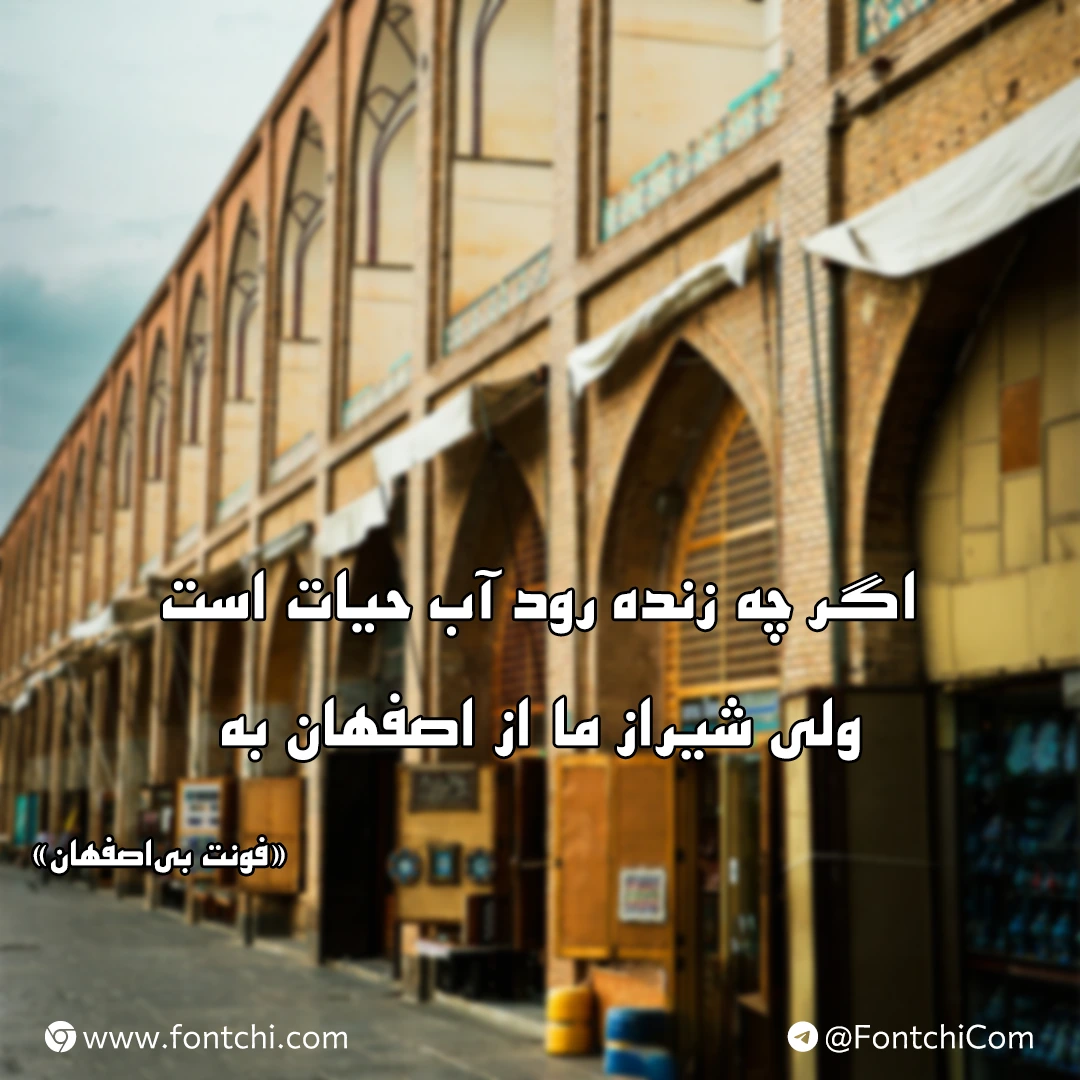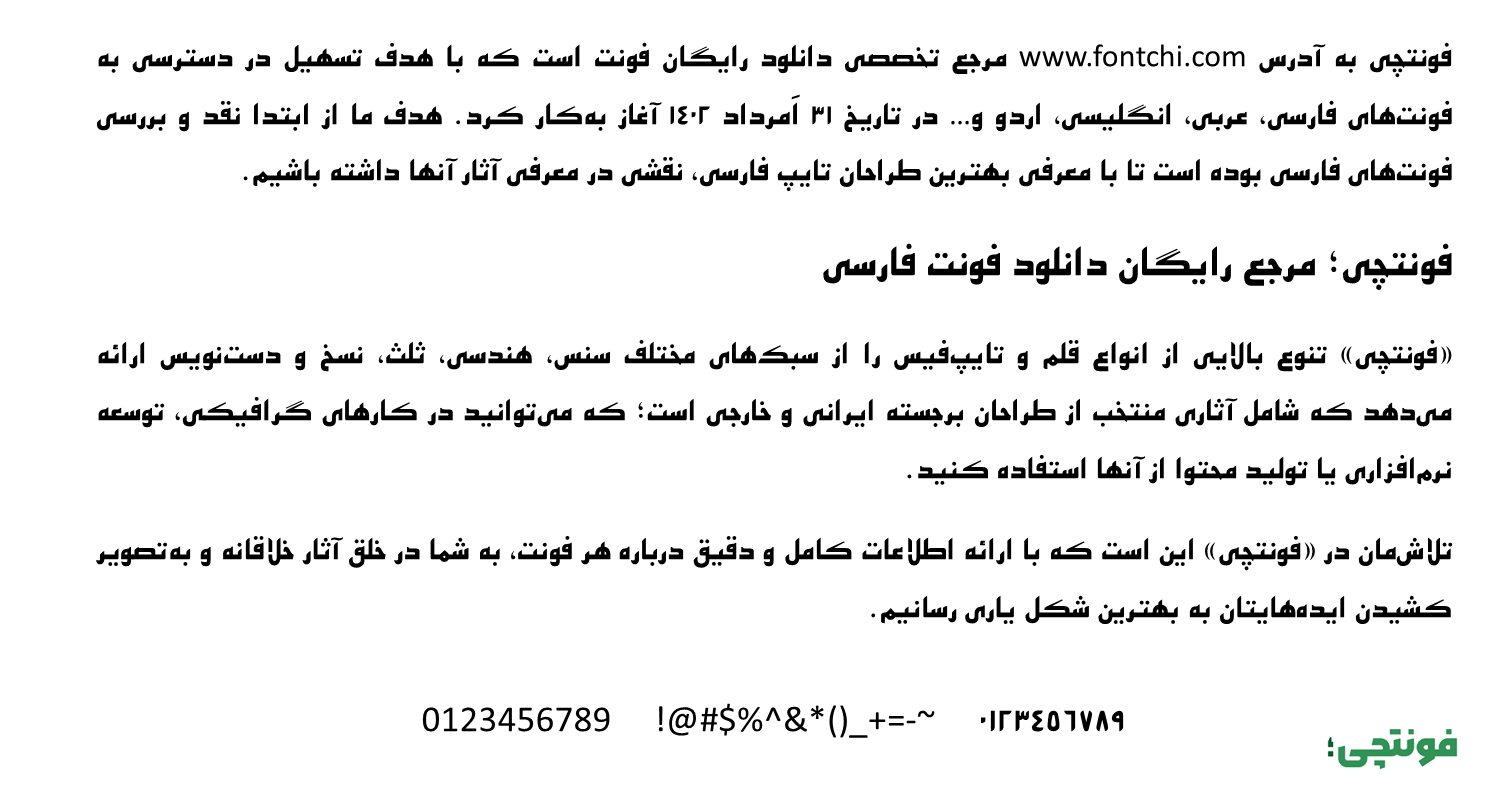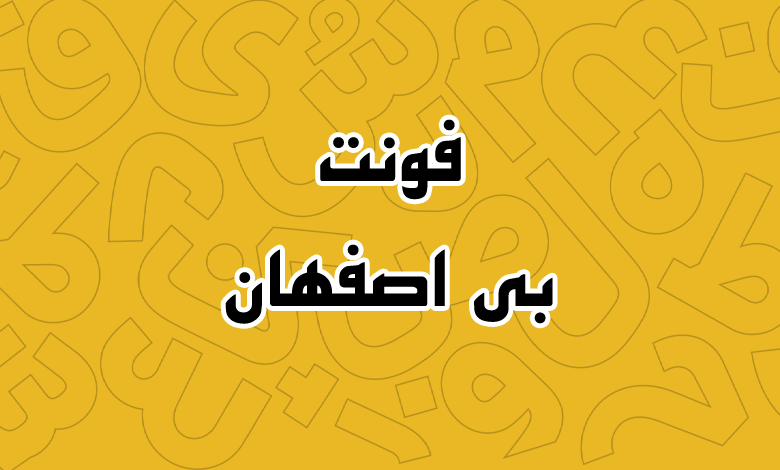
فونت بی اصفهان (B Esfehan)
فونت بی اصفهان یا اصفهان (به انگلیسی: B Esfehan) از دیگر فونت‌های آزاد طراحی‌شده توسط برنا رایانه است که برای استفاده در متون فارسی توسعه یافته است. این فونت با ساختار کلاسیک و سنتی، الهام‌گرفته از خطوط قدیمی ایرانی است که به‌طور خاص برای استفاده در عناوین و تیترها طراحی شده است.
در طراحی فونت بی اصفهان حروف دارای انحنا و قوس‌های ظریف هستند که یادآور خطوط سنتی ایرانی می‌باشند. طراحی حروف به‌گونه‌ای است که حس اصالت و قدمت را به مخاطب منتقل می‌کند.
فونت بی اصفهان بولد (Bold) تنها همین وزن را دارد که آن را برای استفاده در عناوین و تیترها مناسب کرده است. ضخامت حروف به‌گونه‌ای است که جلب توجه کرده و در عین حال خوانایی را حفظ می‌کند. این فونت به‌طور کامل از حروف فارسی و عربی پشتیبانی می‌کند و تمامی اتصالات و ترکیبات حروف به‌درستی نمایش داده می‌شوند.
تنها ایراد این فونت در بخش اعداد است که در زبان فارسی نیز اعداد عربی «۰۴۵۶» به‌کار رفته است. اما در بخش حروف عربی «ک، ی، ه، ؤ، ئ» شاهد گلیف‌های استاندارد برای این زبان هستیم. برای زبان انگلیسی نیز فاقد طراحی اختصاصی است و از فونت پیش‌فرض سیستم عامل استفاده می‌شود.
با توجه به ویژگی‌های این قلم، از فونت b esfehan می‌توان در موارد زیر استفاده کرد:
• استفاده در عناوین کتاب‌ها، مقالات و نشریات برای ایجاد تاکید و جلب توجه؛ خصوصا باموضوعات تاریخی، فرعنگی و هنری.
• مناسب برای طراحی لوگوهایی به سبک سنتی و کلاسیک که نیاز به انتقال حس اصالت دارند.
• استفاده در پوسترها و بنرهایی که نیاز به جلب توجه سریع مخاطب دارند.
• مناسب برای تابلوهایی که نیاز به فونت‌های با خوانایی بالا و جذابیت بصری دارند.
حروف فونت بی اصفهان دارای طراحی دقیق و کاملا خوانا هستند که اصالت فرهنگ ایرانی را در اندازه‌های مختلف انتقال می‌دهند. این فونت برای کارهای فرهنگی و هنری، جذابیت خاصی به پروژه‌های گرافیکی شما خواهد داد.